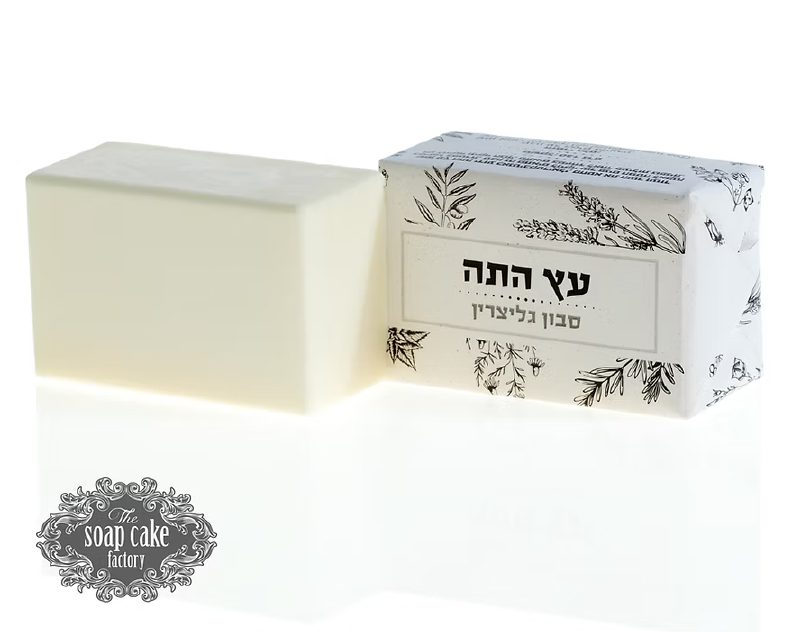
פלאשבק
פלאשבק / Flashback
• שם הגופן:פלאשבק
• מעצב הגופן:נדב עזרא
• סגנון:סלאב סריף
• קטגוריה: עברית ראווה
• מאפיינים: רגיל כבד שחור
• תכונות: חושני מרובע נוסטלגי